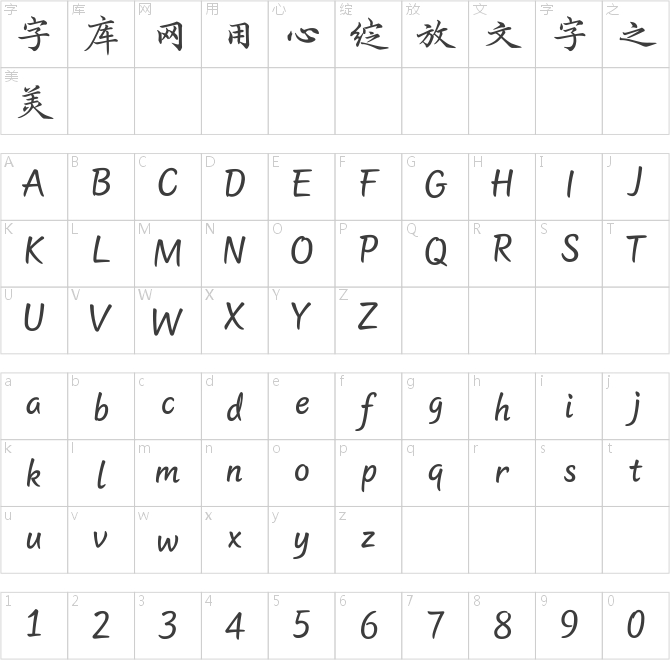
字體名稱: 字酷堂鴻昌楷書
字酷堂鴻昌楷書簡
字酷堂鴻昌楷書字形源自古籍《岳雪樓書畫錄》(清光緒十五年南海孔氏三十有三萬卷堂精寫刊本)。《岳雪樓書畫錄》由清代藏書家孔廣陶編。全書共五卷,收錄孔氏岳雪樓藏唐宋至明名家書畫一百三十八件,書中對每件作品詳載紙絹尺寸、收藏印鑒、諸家題跋。間有作者自題、記得畫經(jīng)過、品評鑒賞等。此為清光緒十五年南海孔氏三十有三萬卷堂精寫刊本。孔氏為粵東大族,頗富資財(cái),好金石書畫,筑岳雪樓藏之。是書錄自藏書畫真跡自唐及明,劇跡甚多,選錄亦較精審。法書有唐人書《藏經(jīng)》墨跡冊《六法大成》冊尚有宋蘇軾、黃庭堅(jiān),元趙孟頫、鮮于樞,明文徵明、董其昌、祝允明、王寵、王守仁、倪元璐等數(shù)十家。書仿《江村銷夏錄》體例,亦錄有原文并題識。此書由番禺周浚霖手書上板,寫刻精妙。卷末有:羊城西湖街富文齋刻字 二行。